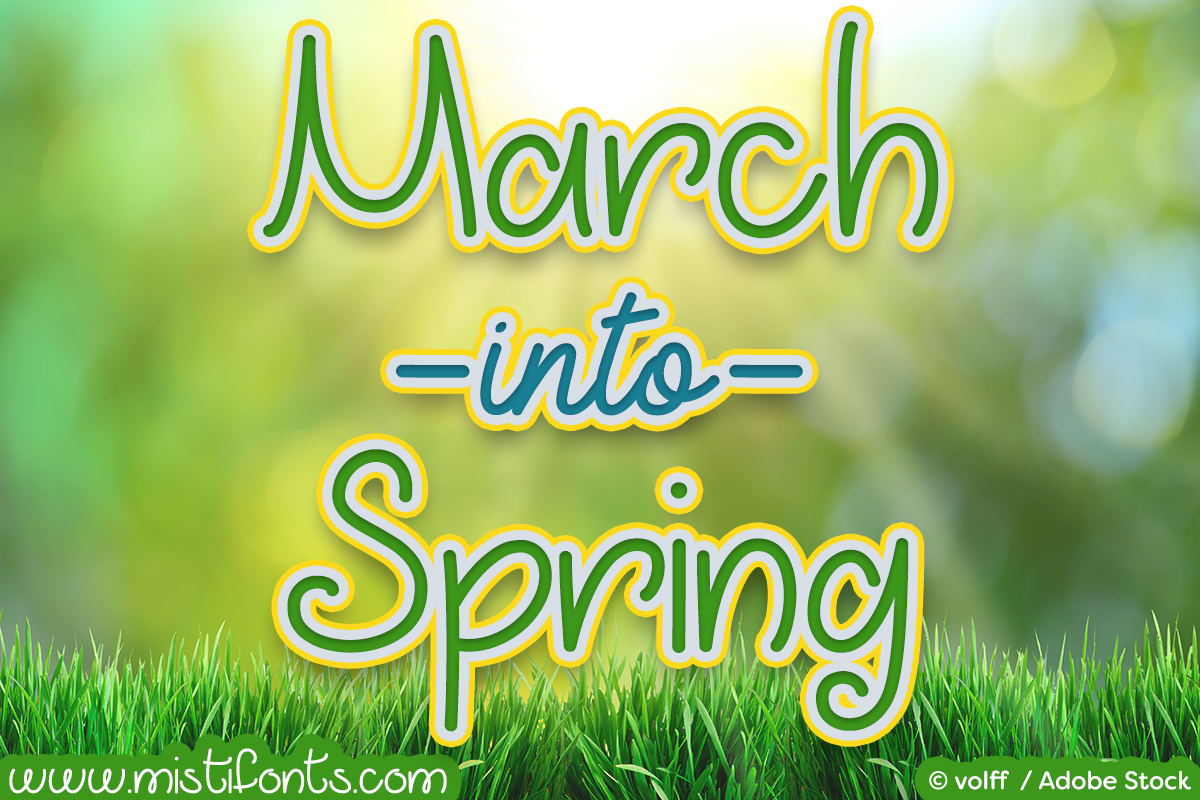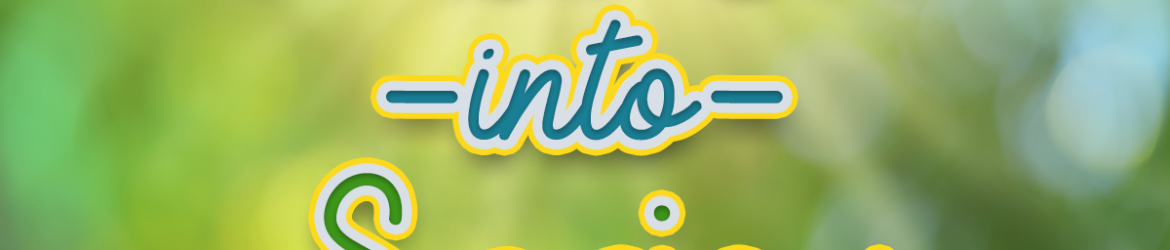
March into Spring Font – Download Grátis
A March into Spring Font é uma fonte à mão livre introduzida pela Misti’s Fonts que traz ao seu trabalho criativo um toque de originalidade e elegância, certamente ideal para diversos usos. Desenvolvida e compartilhada por Misti’s Fonts, a March into Spring oferece uma experiência autêntica da escrita à mão, perfeita para incorporar em trabalhos que exijam um ar cuidadosamente personalizado. Com seu estilo de escrita à mão única e não replicável, esta fonte é especialmente adequada para usar em citações, cartazes, convites de casamento, identidades de marca, logotipos, criação de moda, roupas e acessórios, letras menores e materiais de festa. E se você está buscando dar um toque especial a suas mensagens mais pessoais ou eventos especiais, então March into Spring pode ser exatamente o que você precisa para criar algo único e memorável. Com sua sofisticação e delicadeza, March into Spring é uma fonte perfeita tanto para aqueles que desejam um aspecto de autenticidade em seus trabalhos quanto para designers que buscam a liberdade criativa de usar elementos que remetem à escrita à mão. Experimente essa maravilhosa opção e deixe sua marca pessoal se destacar, seja em um documento profissional ou na criação de uma peça artística única.